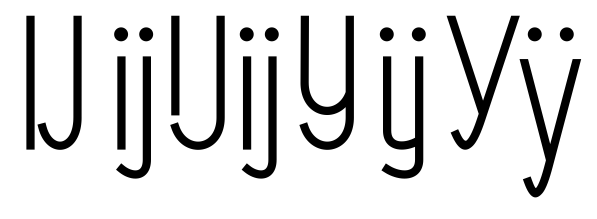
in der niederländischen Sprache gibt es ja eine eigene Ligatur das Versale IJ.
Gibt es so eine Ligatur auch für das kleine ij und wie würde diese aussehen?
So wie ich das in vielen Schriften gesehen habe, gibt es sowohl als Großbuchstabe als auch für die Gemeinen durchaus mehrere Varianten, angefangen von ganz normalem IJ / ij, nur das die eine Glyphe sindüber eine Form, due wie ein "rundes y", also wie ein u mit der Unterlänge des g aussieht, und als Kleinbuchstabe dann die i und j Pünktchen hat bis hin zum У / Y / ÿ
Anscheinend ist das wohl sehr variabel, ich hab dieWarianten mal gezeichnet
Die Frage finde ich interessant. Daher habe ich mal meine Schriften durchgeschaut. Auf die Schnelle konnte ich nur wenige Schriften finden, bei denen sich die Buchstabenfolge I und J bzw. i und j von den Ligaturen IJ bzw. ij unterscheiden. Ein Klick auf das Bild öffnet eine pdf-Datei mit meinen Funden. Es sind mehr als auf dem Ausschnitt oben zu sehen sind.
Nun, dass in so vielen Schriften kein nUnterschied zwischen IJ /ij als einzeln gesetzte Lettern und den Ligaturen zu sehen ist (außer natürlich dem Umstand, dass dann in der Ligatur nicht getrennt werden kann), kann natürlich auch damit zusammenhängen, dass die meisten Schriftarten eben außerhalb der Niederlande und auch nicht von einem niederländischen Schriftgestalter entwickelt wurden.
Vor etwas längerer Zeit war hier mal ein Link zu einer Flikr-Seite mit Fotos von niederländischen Ladenschildern und anderen Beschiftungen im Niederländischen Straßenbild, und dort waren die mehr in Richtung Y gehenden Formen des IJ deutlich häufiger vertreten.
Gut möglich, dass vielen Schriftgestaltern hier auch die Information über die möglichen - und möglicherweise bevorzugten Formen fehlt, und dann eben gedacht wird: "Wenn ich für die IJ-Ligatur einfach nur I und J auf einen Kegel packe, liege ich bestimmt auf der sicheren Seite, so falsch kann das sicher nicht sein.
Ähnliches habe ich auch schon beim Ogonek beobachtet, auch hier sind in richtig guten, professionellen Schriften trotzdem schechte, ja sogar falsche Umsetzungen zu finden, weil die Gepflogenheiten der Länder, die Schriftzeichen mit dem Häkchen dran verwenden dem Schriftgestalter unbekannt waren, und er das dann eben nach Gefühl gemacht hat.
Gerade die Schriften von van Krimpen (Van Dijck, Spectrum), Unger (Swift, Demos, Praxis), Noordzij (Caecilia) oder de Groot (Thesis) haben bezüglich der IJ-/ij-Ligaturen gar keine Auffälligkeiten.
Als Niederländer würde ich sagen das ij kein richtiger Ligatur darstellt, sondern ein Diphtong. Es gibt auch keine eigene Taste auf niederländische Tastaturen und er wird auch nicht als zusammengesetzt geschrieben. Der ÿ ist soweit ich weiß falsch, und wird wahrscheinlich nur aus aus Unwissenheit oder aus technische Einschränkungen (von z.B. Displays) benutzt.
Ich denke das der Ligatur in Satzschriften ein Relikt ist aus Bleisatz-Zeiten, wo häufig vorkommende Paare wie z.B. /ch/ im Deutsch zusammengenommen wurden. Das sparte Zeit und Geld. Meistens wird der Kombination ij auf Niederländisch ein wenig enger gestellt als sonst, aber besteht keine Notwendigkeit für eine Ligatur, außer aus dekorativen Gründen.
Es gibt nicht wenige, die ij auf die Art handschriftlich schreiben.
Ich kann’s mir nicht verkneifen, auch hier wieder darauf hinzuweisen, dass Ligatur erstmal nur »Verbindung« heißt und nicht zwangsläufig darüber sagt, ob nun etwas sprachlich, grafisch funktional, grafisch schmückend oder drucktechnisch verbunden wurde. All das ist möglich. Ohne genauere Definitionen oder eindeutigen Kontext muss man also immer sehr vorsichtig sein, etwas generell als Ligatur oder Nicht-Ligatur bezeichnen zu wollen.
Ok, das stimmt.
Ich bleibe aber dabei das der IJ Ligatur keine typografische notwendigkeit hat, sondern eher druckhistorische Ursprünge hat.
Was ÿ angeht, es stimmt das in geschriebene form ij manchmal so aussieht wie ÿ. Im Druck kommt sowas nur selten vor.
Übrigens muß ich mich selbst korrigieren: bei Schreibmaschinen mit gleiche Buchstabenbreiten gab es früher aus platzsparenden Gründen auch ein IJ als eine Buchstabe. Bei Computertastaturen aber nicht mehr.
Auf der Niederländische Wikipedia ist übrigens zu lesen das der ij ligatur aus kompatibiltätsgründen mit ältere Kodierungssysteme aufgenommen wurde, von dessen Gebrauch aber abgeraten wird.
Ähm, ein Diphthong ist eine ganz andere Kategorie als eine Ligatur. Ersteres bezeichnet Laute, zweiteres Zeichen.
Zumindest für das große IJ scheint es mir (als Nicht-Niederländer) z. B. bei kalligrafischen oder gebrochenen Schriften sinnvoll, eine Ligatur zu haben, da zwei normale Großbuchstaben unschön überdimensioniert sein können. Siehe z. B. die Beispiele in Underwares IJ-Artikel (der hier übrigens auch generell von Interesse sein könnte).